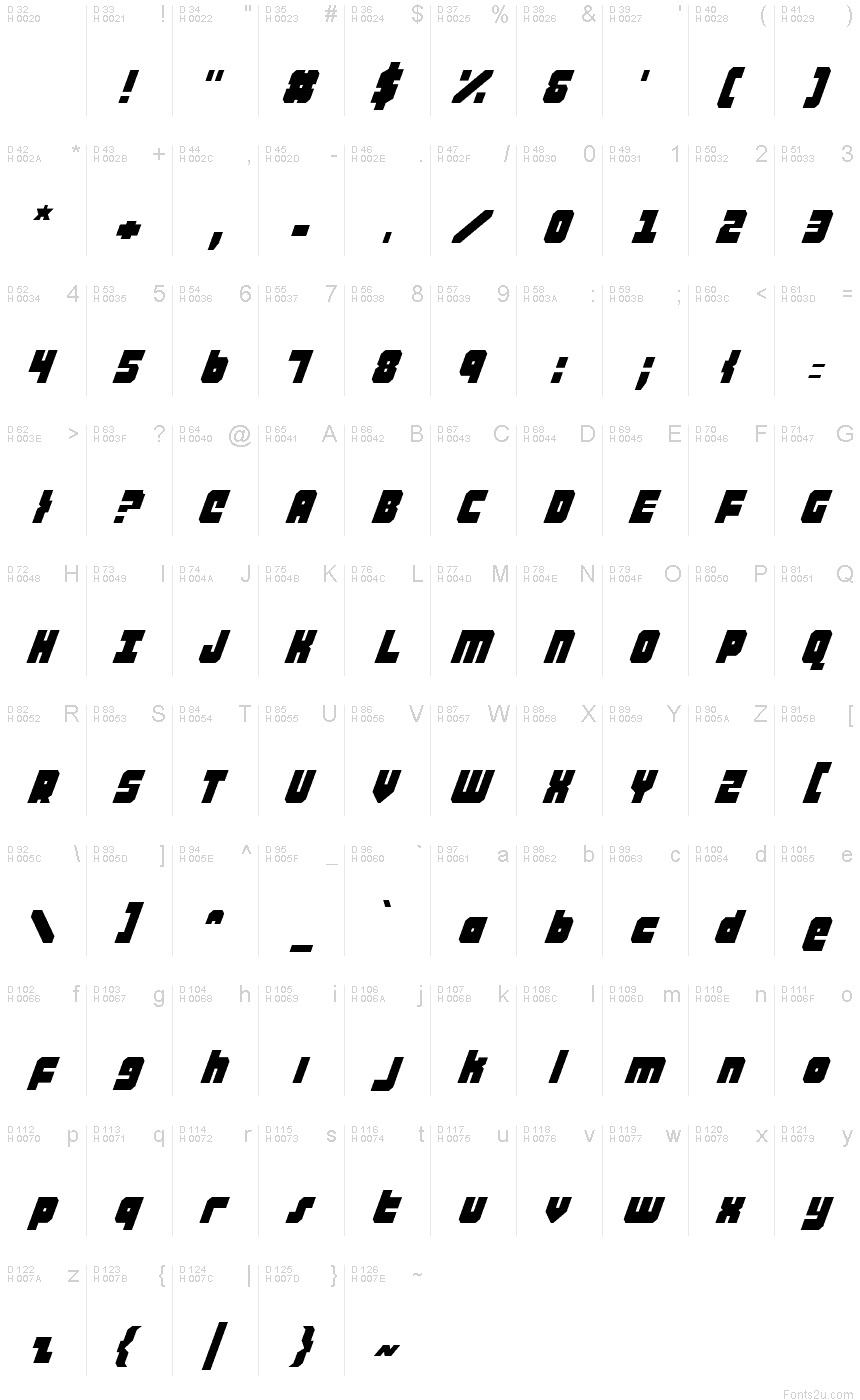
Alpha Taurus Italic od Iconian Fonts to darmowy, pochyły krój techno display o futurystycznym, ostrym charakterze. Litery pochylają się do przodu w grubych, wyrazistych formach, łącząc ostre przekątne ze ściętymi narożnikami. Dzięki temu font sprawia wrażenie szybkiego, mechanicznego i nawiązującego do ery arcade, nie wpadając przy tym w retro parodię.
Naturalnie odnajduje się w logo gier, plakatach sci-fi, brandingu e-sportowym, planszach tytułowych i mocnych nagłówkach, gdzie krótkie słowa potrzebują ruchu i dynamiki. Jako darmowy font, świetnie sprawdza się również w nagłówkach interfejsów, grafikach dla streamerów i kompaktowych znakach słownych, ponieważ jego kanciasta sylwetka nadaje nawet prostemu tekstowi naładowany, kierunkowy impet.